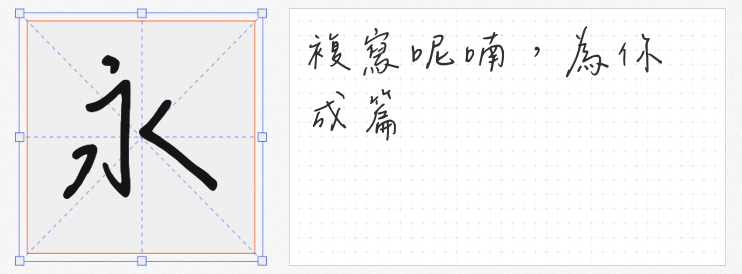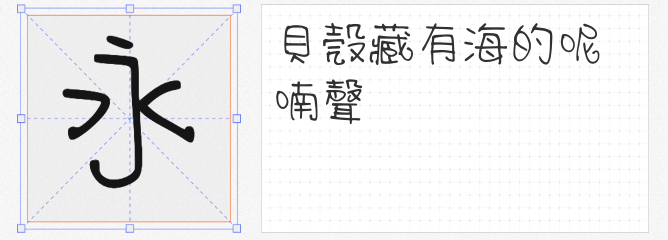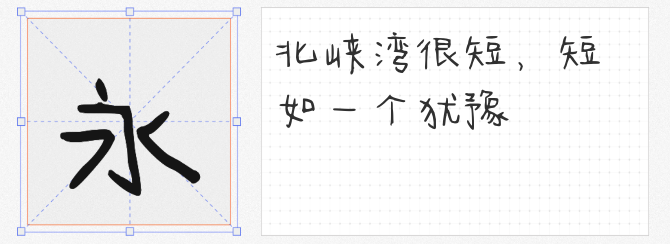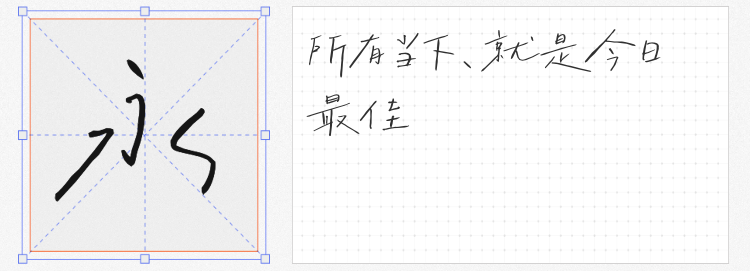
在设计的创意世界里,手写字体宛如灵动的精灵,以其清新简约的风格,为作品注入独特魅力。今天就为大家推荐四款免费商用的手写字体,让你的设计轻松脱颖而出。
1. 字制区喜脉喜欢体
这款字体自带文艺气质,笔画自由洒脱,仿佛书写者随心而动的创作。它特别适合作为字数较少的大标题,在自媒体封面标题中,能瞬间抓住读者眼球;在音乐专辑封面,可营造出浪漫的氛围;电影海报上,它能为画面增添艺术感;杂志排版里,又能展现独特的个性。其自由奔放的风格,让每一个标题都成为视觉焦点。
2. 清松手写体6
由游清松在稿纸上用原子笔手写,再经字体软件加工而成,这款字体没有电脑字型的生硬感,满是手写的自然与温暖。作为繁体手写字体,它在设计中能营造出亲切的氛围。在传统风格的宣传海报、复古风格的明信片设计,或是需要展现人文气息的书籍封面中,清松手写体6都能完美融入,为作品增添一份质朴的韵味。
3. 辰宇落雁体 Thin Monospaced
这是作者与韦辰合作完成的字体,韦辰书写,作者后制,二者默契配合成就了这款优雅又俏皮的字体。它的大小不一的笔画,打破了常规的规整感,带来灵动的视觉效果。在高端品牌的宣传物料、文艺风格的邀请函,或是需要展现精致感的网页设计中,辰宇落雁体都能展现出独特的魅力,让设计既有优雅的气质,又不失俏皮的趣味。
4. 今年也要加油鸭
笔画出头较短,构字骨架充满童稚感,这款字体整体笨拙可爱,仿佛带着孩童的天真无邪。它非常适合少儿类、萌宠类、美食类的广告和产品包装设计,能瞬间拉近与受众的距离。在社交网络上,作为个性化用字,也能让你的表达更加生动有趣,展现出满满的萌趣感。